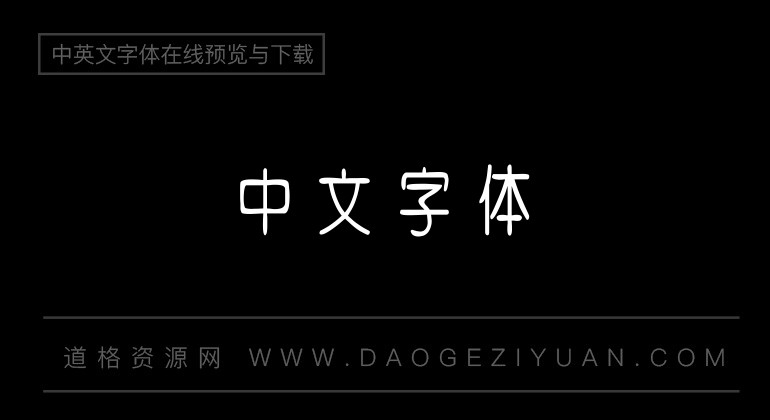
金梅中圆原体国际码
金梅中圆原体国际码字体是一款由香港设计师金梅设计的字体,它的特点是圆润的原体,让文字看起来更加圆润,更加简洁。字体采用了国际码,能够支持多种语言,使用起来也更加方便。此外,金梅中圆原体国际码字体还具有良好的可读性和可视性,能够更好地表达文字的意义,让文字更加精致。
金梅中圆原体国际码是一款非常不错的手写艺术字体,具有很好的视觉感,适合于文化类的宣传设计、商业类品牌的广告和产品包装设计以及个性化文字排版等较多场景。